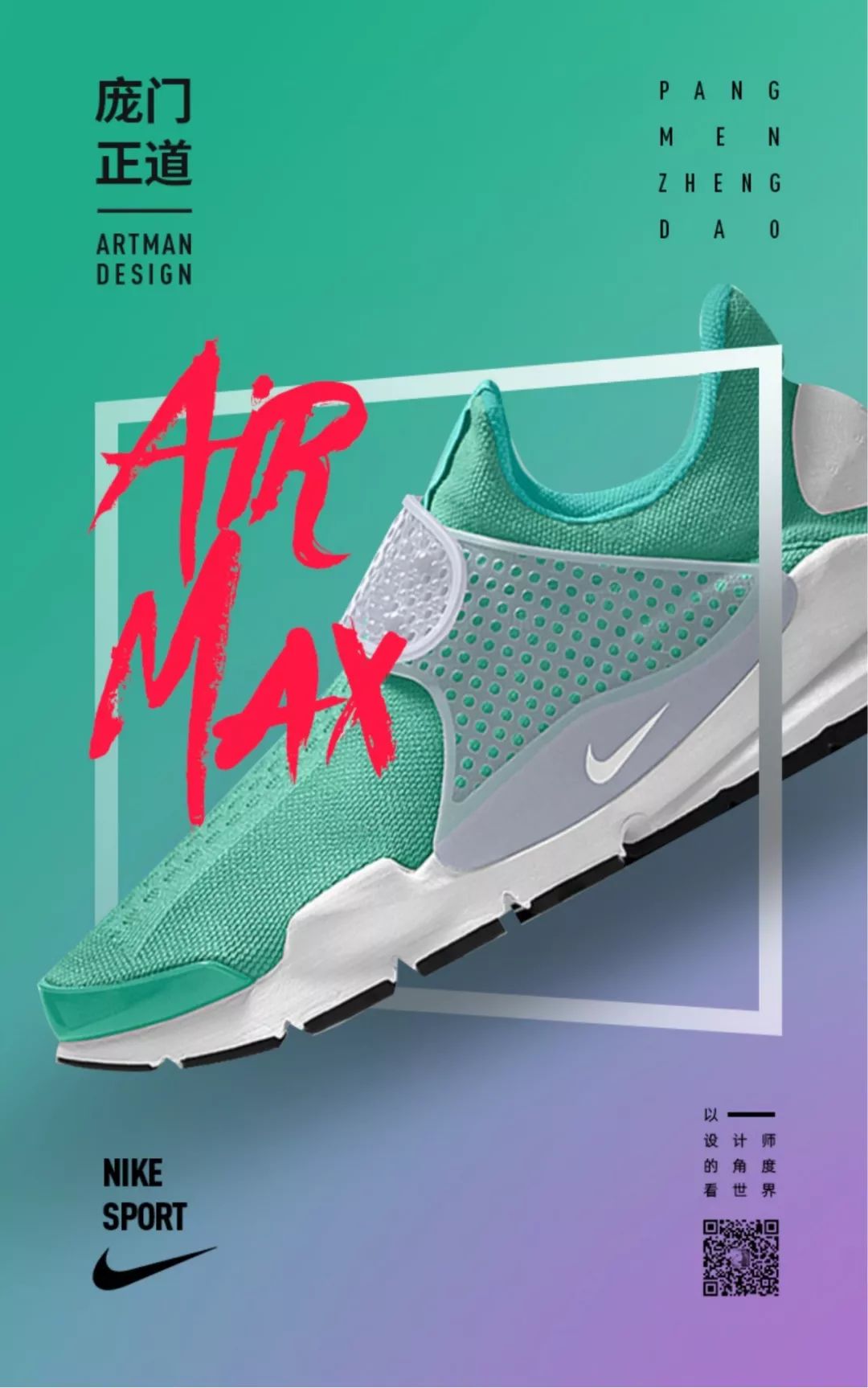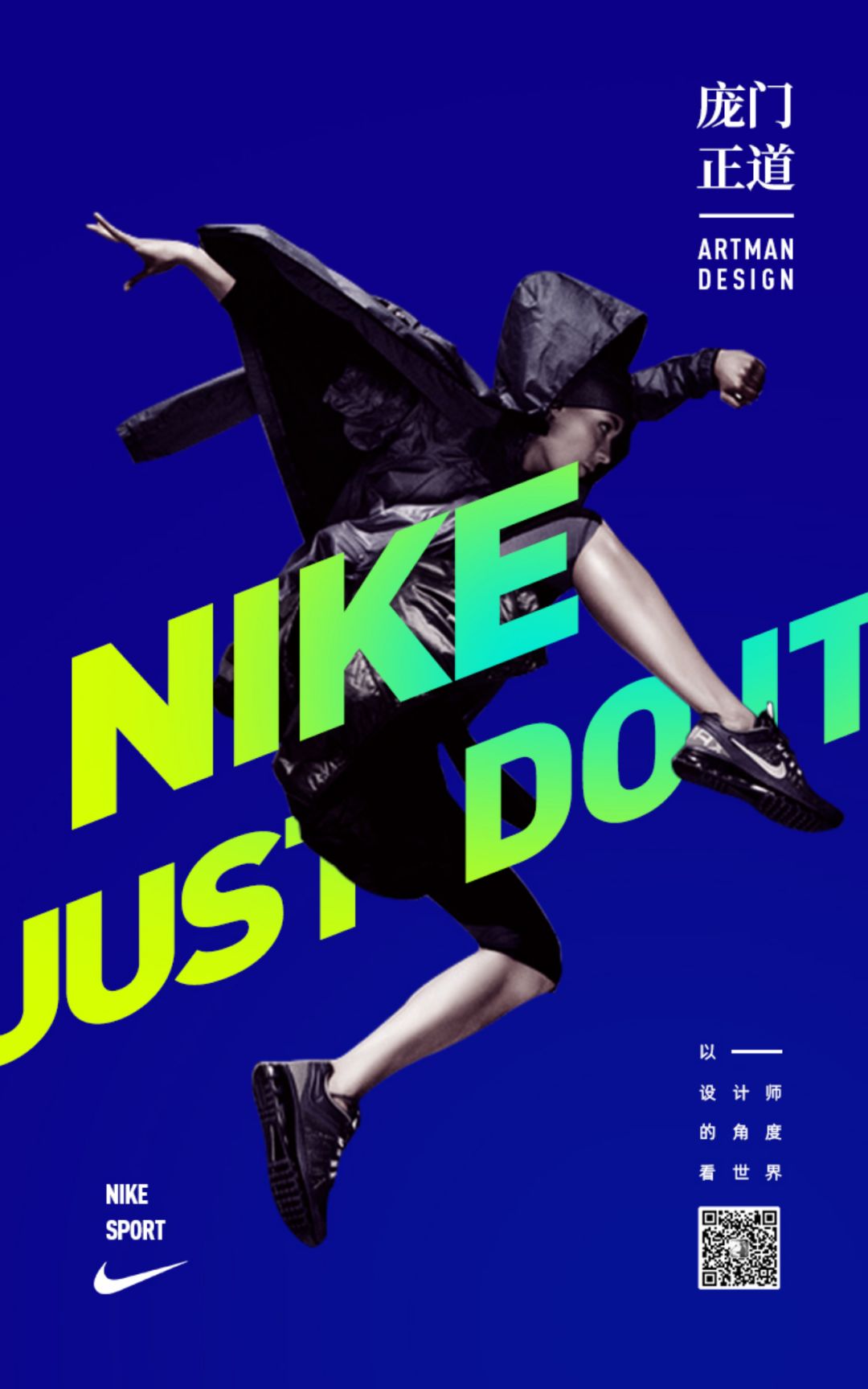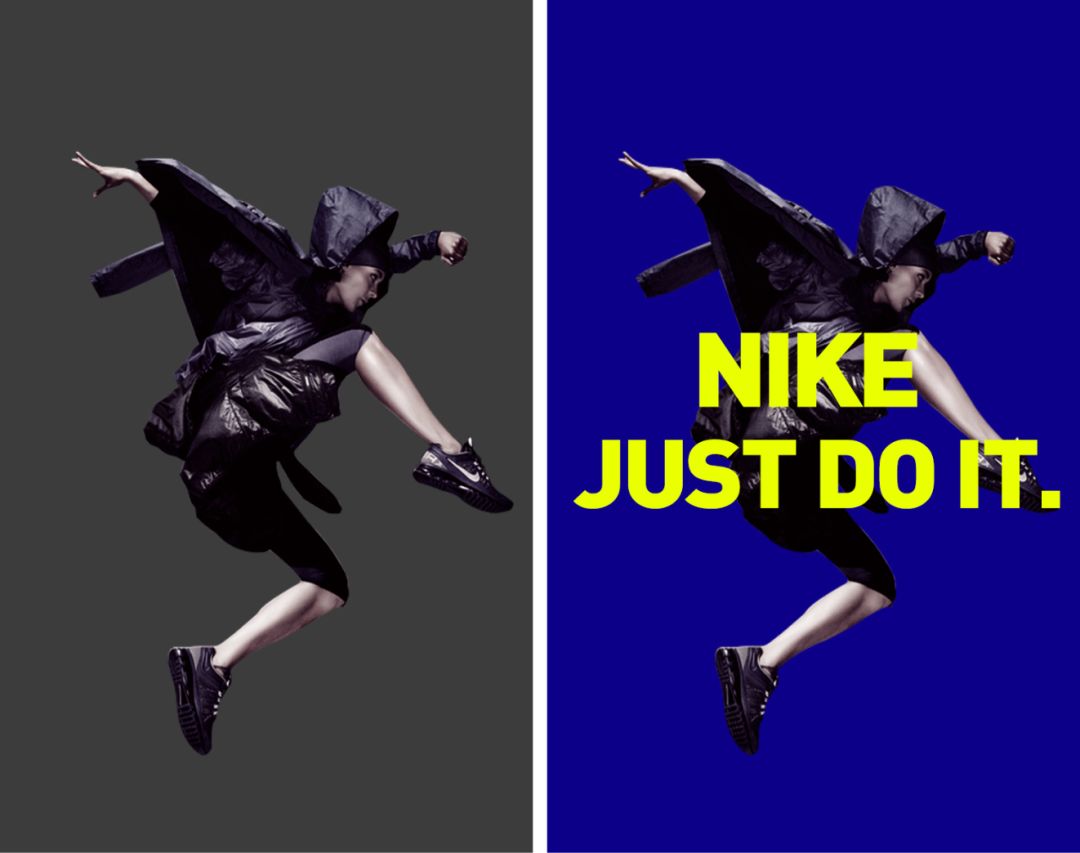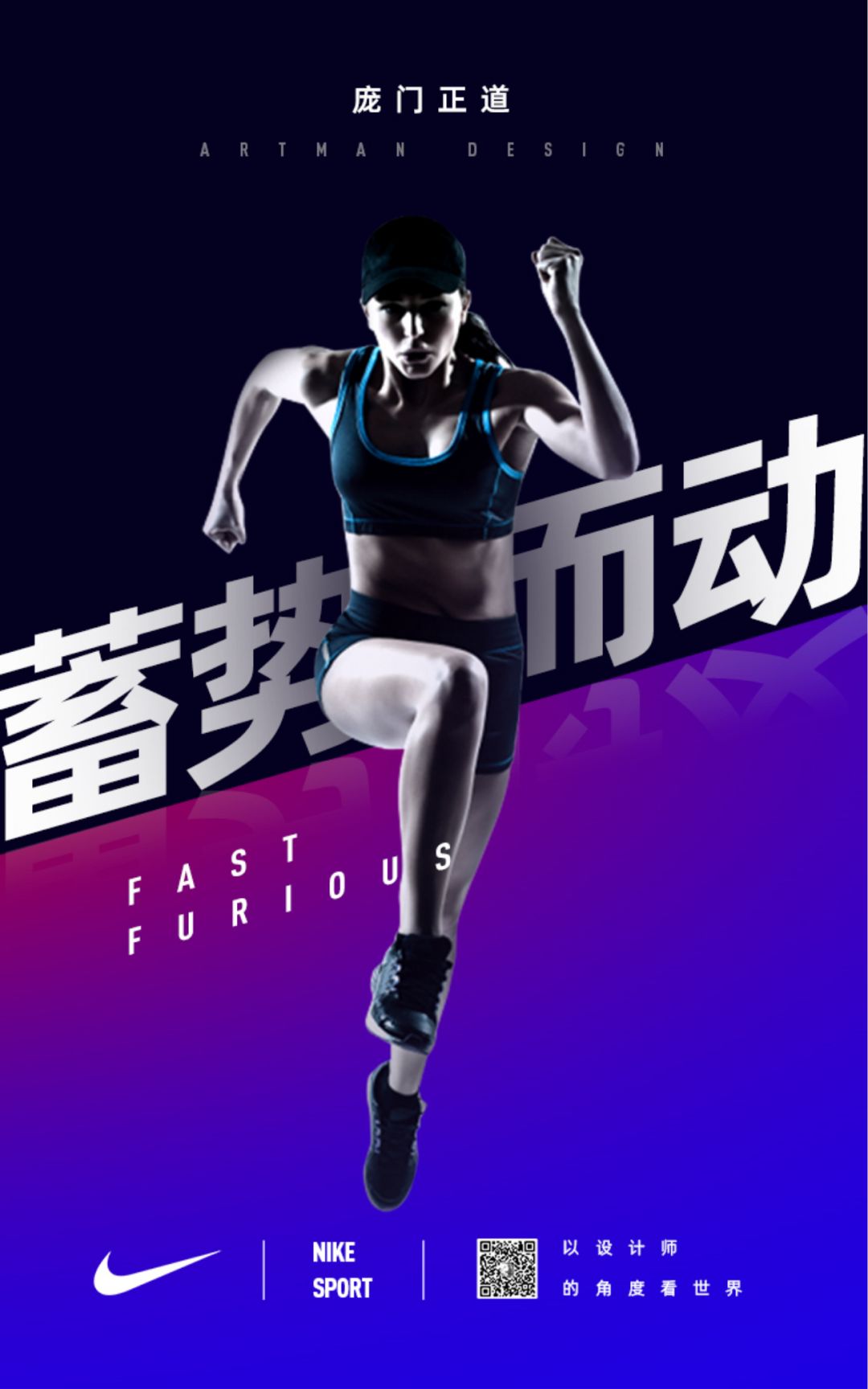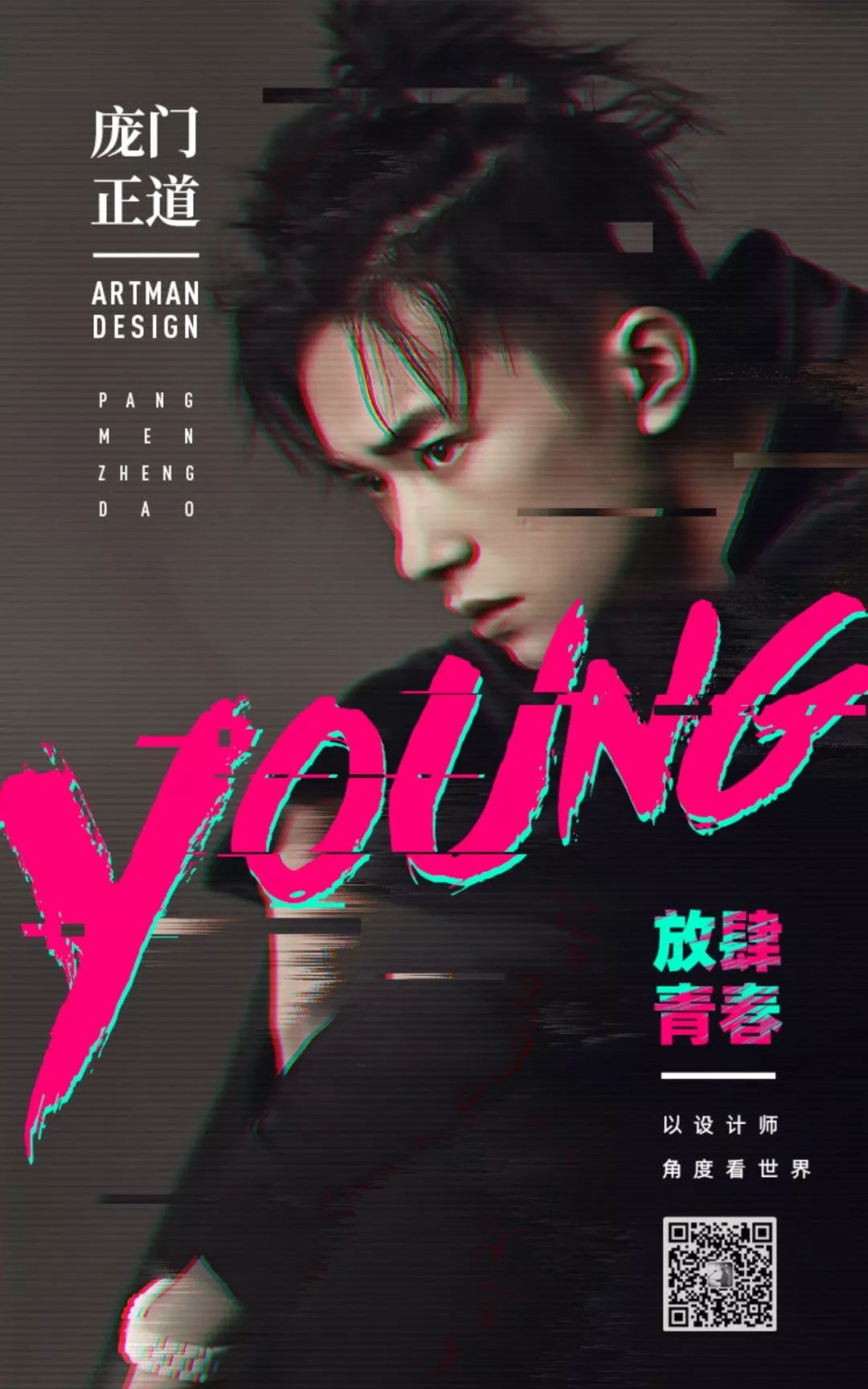
如何提升视觉冲击力?四招学会动感设计
在一些营销活动,和电商广告中,我们会经常提到一个词——视觉冲击力。
要提升视觉冲击力,我们第一时间就会想到刺激的颜色,超大的字号等等。
No!No!No!
不是这个意思!
听我继续说,
这些方法都可以提升画面的力度,还有另外一种方法,那就是提升画面的速度感,也就是让画面富有动感。
艾瑞巴帝,动起来!
所谓的动感,并不是说让画面动起来,而是指通过排版的变化,让元素之间形成律动,从而带来的视觉上的跳跃感。
富有动感的画面,可以更加的吸引用户的眼球,能更快速的将重要信息传达给用户。在运动、男性类的设计主题中经常会用到。
下面我们就从平面构成的原理上来分析,看看用哪些方法可以给画面带来运动感。
看招吧!
我们都知道,整齐、规律的排列方式可以带来视觉上稳定、静止的感觉。
那相对应的,不整齐、不规则就可以造成不稳定,从而形成动感。
比如说下面这个简单的例子:
我们来看看具体的设计案例:
一只鞋歪了,平静的排版被破坏,画面就动起来了。
手的介入,把画面静止打破。
破坏规则的几何图形,也能形成运动感,我们常把这种方式称之为破版。
破版的设计手法,在海报设计中几乎随处可见。
好了,下面就到了案例实操的时间。
在网上找一张运动鞋的素材,抠好图,添加阴影加强立体感。
汲取鞋子的颜色用作背景色,就可以得到一个很和谐的画面。
再将文字信息排版好,海报的雏形就完工了。
OK,最后来个高清大图:
第一招讲到这,
接下来请看第二招。
(少林功夫好)
要让画面显得更有动感,倾斜是最直观有效的方法。
将画面中的元素倾斜之后,会造成不对称、不稳定的状态,这在一定程度上会影响阅读体验。为了克服这些缺点,需要我们在倾斜角度,以及倾斜方式上多做文章。
常见的倾斜方式有以下三种。
第一种是文案或主体倾斜。
这种局部倾斜在整体上在视觉上是比较稳的,只要将主要的文案或者视觉元素倾斜就行。
如果是文案倾斜,注意倾斜角度不要过大,以免影响可读性。
具体案例:
第二种方式是背景倾斜。
背景倾斜只需要将背景元素进行角度变化,就能让整个画面产生强烈的动感。
这种倾斜方式需要注意背景与文字的冲突,尽量让文字不受到背景的干扰。
具体案例:
第三种方式是整体倾斜。
整体倾斜即文案和背景全都是倾斜的,这种方式的视觉冲击力是最强的,但同时也是比较难掌握的一种方式。把控不好,容易导致整个画面过于凌乱。
具体案例:
OK,了解完几种倾斜方式之后,该到了自己动手时间。
先来一个文案倾斜的案例:
先将运动的人物主图抠好。
填充好背景色,打上主标题。这个时候我们发现画面有点生硬。
然后尝试将文案倾斜,再结合人物的肢体动作,跟文案作前后叠压处理。如下图所示:
最后再调整下文案和背景的颜色细节,增加绿色到黄色的过度让画面看起来更有活力,最后将其它文案排版好,就完工了!
好了,最后来看看高清大图:
(是不是动感的时候更爽一些?)
再来看另一个案例。
将人物素材放到画面中,然后添加文案做初步的排版。
排版好了之后,感觉画面有点沉闷,运动感不够强烈。
于是尝试在背景上做一下效果:
在背景上增加倾斜的效果,再加上渐变的颜色之后,整个画面显得更有活力。
看看高清大图:
是不是非常的性感?
哦,不对,动感!
OK,
继续看下一招。
线条的反复、错开,再加上模糊的背景,可以营造出强烈的速度感。
比如说我们常看到的光影效果:
这种效果我们一般用在塑造运动中的物体。
静止的摩托车:
加上错开的线条、模糊的背景之后,瞬间就有了强烈的速度感:
在汽车造型的设计中,我们经常可以看到用错开的线条来营造运动感。
偏商务的车型会强调优雅稳重,线条会更柔和一些:
超跑追求的是速度与激情,所以我们可以看到更多的错开线条,显得更加犀利:
尽管具体表现上会有不同之处,但是原理都是一样的。
好了,回到我们的主题。
模糊错开的设计手法,广泛的应用于游戏、运动类的设计上:
现在很流行的故障艺术风格,大量错位的线条,使得画面很有动感。
我个人比较喜欢这种轻度一些的故障风格,不会破坏画面原有的内容。
下面我们的实操案例就做一个类似效果。
首先在网上找一张易洋千玺小哥哥的帅照,然后做出重影的效果:
重影效果的做法如下:
第一步,复制一层,然后调出“图层样式”面板,在通道那里只勾选其中一个通道。
第二步,将该图层往左移动一些,你就会发现重影效果出现了。
用同样的方式再做一层,勾选另一个通道,然后往右边移动一些。这样重影的效果就出来了。
接下来我们给照片添加条纹的肌理,将条纹素材的图层用“柔光”模式叠加上去即可。
再用 滤镜 > 风格化 > 风... 这个滤镜,将照片的局部做一点横向模糊的效果。如上面右图所示。
然后将图层合并,做一点错开的效果(注意不要破坏小哥哥的颜),如下左图所示:
最后再将文案排版好,就大功告成!
看下高清大图:
帅不帅?
OK,
继续看下一招。
弧线天生具有强烈的动感。
尤其是一组线条向一个终点聚集的时候,会很自然的形成画面焦点,对视线有着强烈的引导效果。
不止弧线,弧形的形状也会有一种强烈的动感:
来看看应用弧线的具体优秀设计案例:
弧线的动感是一种温和的流动感,相对来说没那么强的视觉冲击力,不过弧线所带来的视觉上的起伏感会给人很灵动的感觉。
接下来的实操案例我就将弧线元素与书法汉字线条相结合,做一张庞门正道的海报。
我选择以汉字“道”作为主体,体现“设计之道”的海报主题。
首先找一个在线条上比较流畅的“道”字,然后对局部进行改造,将道字的最后一笔与弧形相结合,形成一种缓缓流淌开的视觉效果。
视觉主体做好之后,给背景上添加类似宣纸的肌理,再将文案排版好。就完工了!
最后看看高清大图:
好了,
最后,我们来回顾一下营造动感效果的四种方式:
一、破坏
二、倾斜
三、模糊、错开
四、弧线